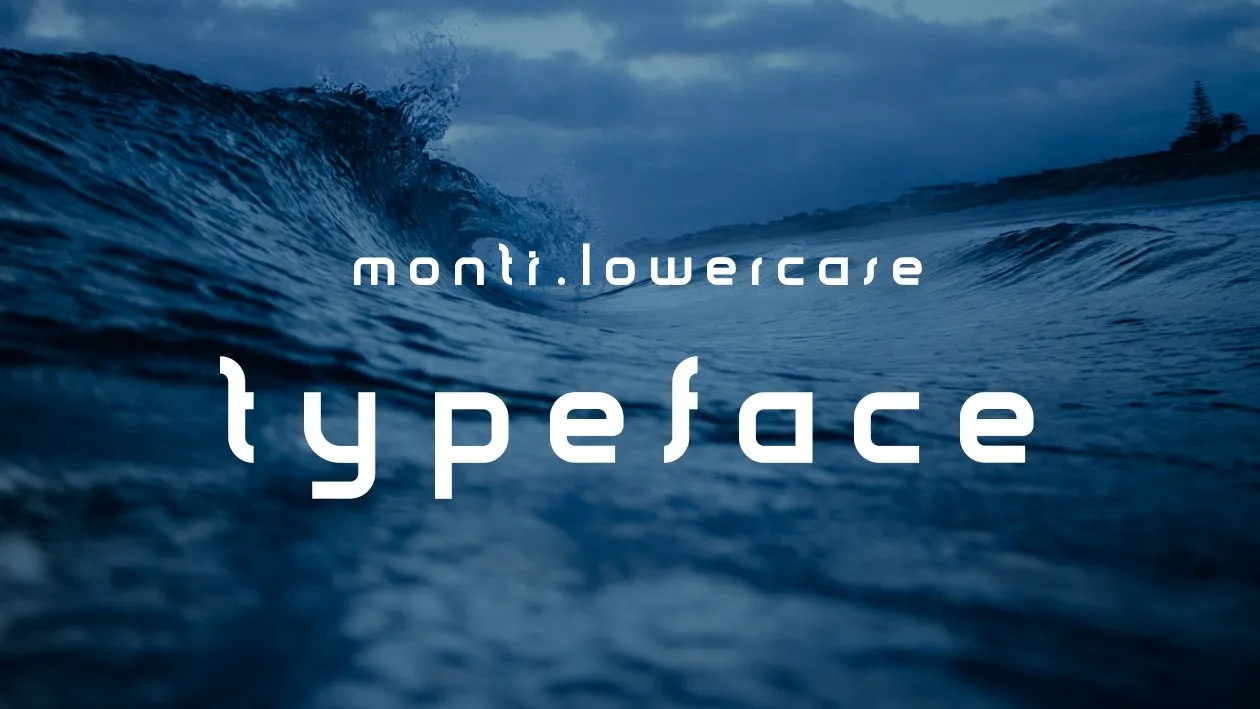
Monti Font – Download Grátis
A Monti é uma nova fonte sans serif com pesos iguais e minimais, perfeita para criações de logotipos minimalistas, nomes de marca ou uso no branding. Sua simplicidade a torna versátil para aplicações variadas, como logos, rótulos de produtos, selos postais e materiais promocionais em geral. Com uma paleta limitada ainda que atualmente apenas contendo letras minúsculas, o plano do desenvolvedor é expandi-la com alfabeto maiuscula nos próximos meses. Esta fonte está disponível de graça tanto para uso pessoal quanto comercial, fazendo-a um recurso valioso para designers e empresas em busca de uma opção moderna e minimalista.